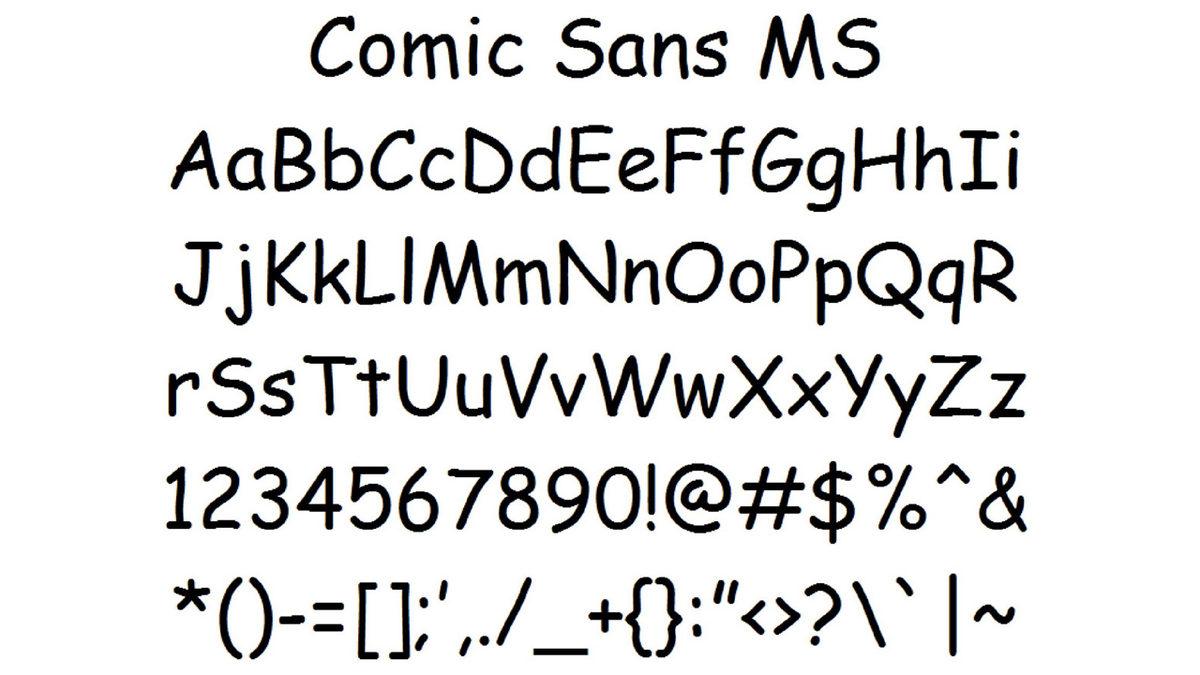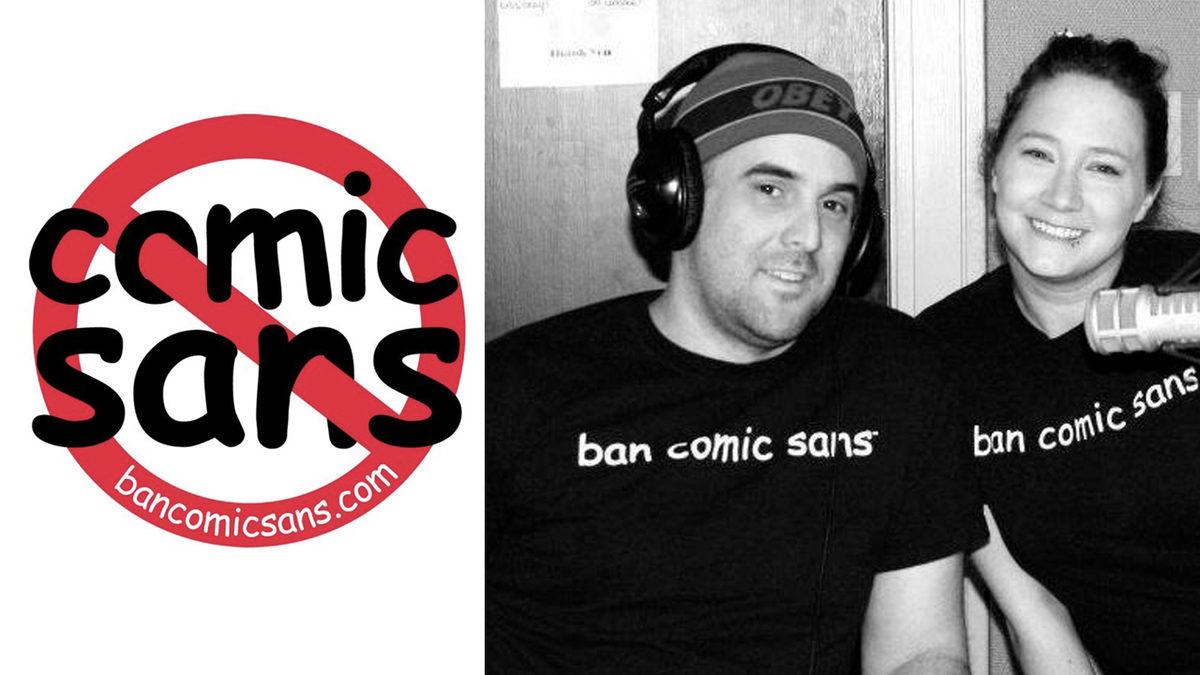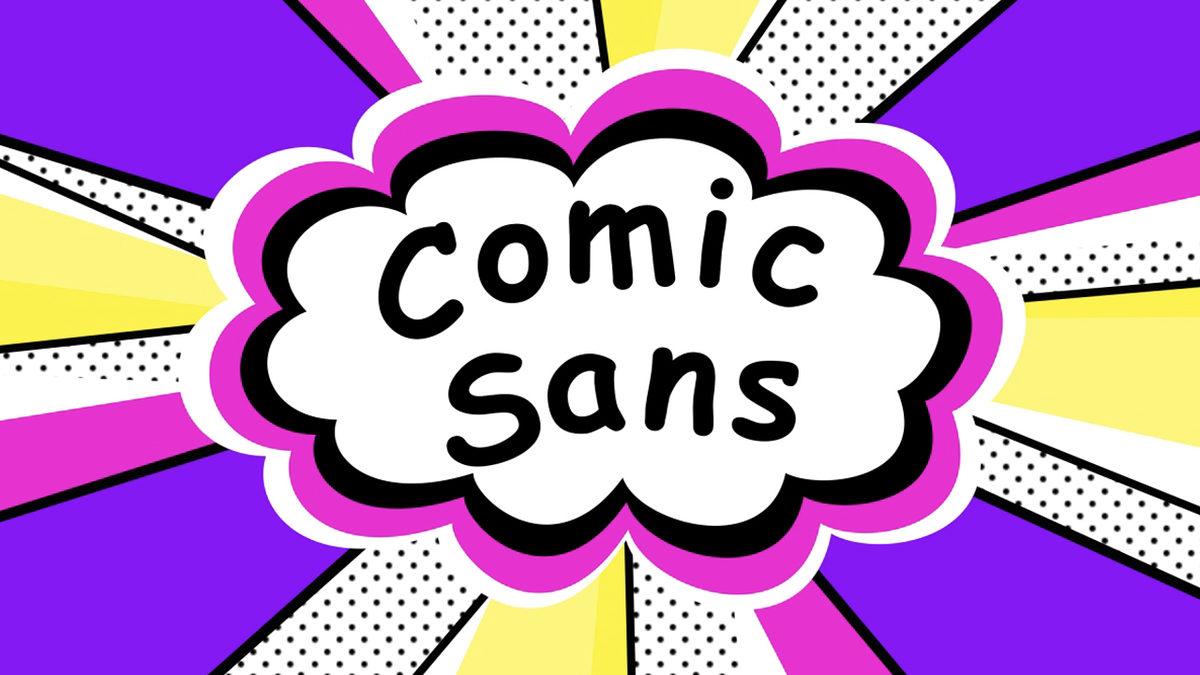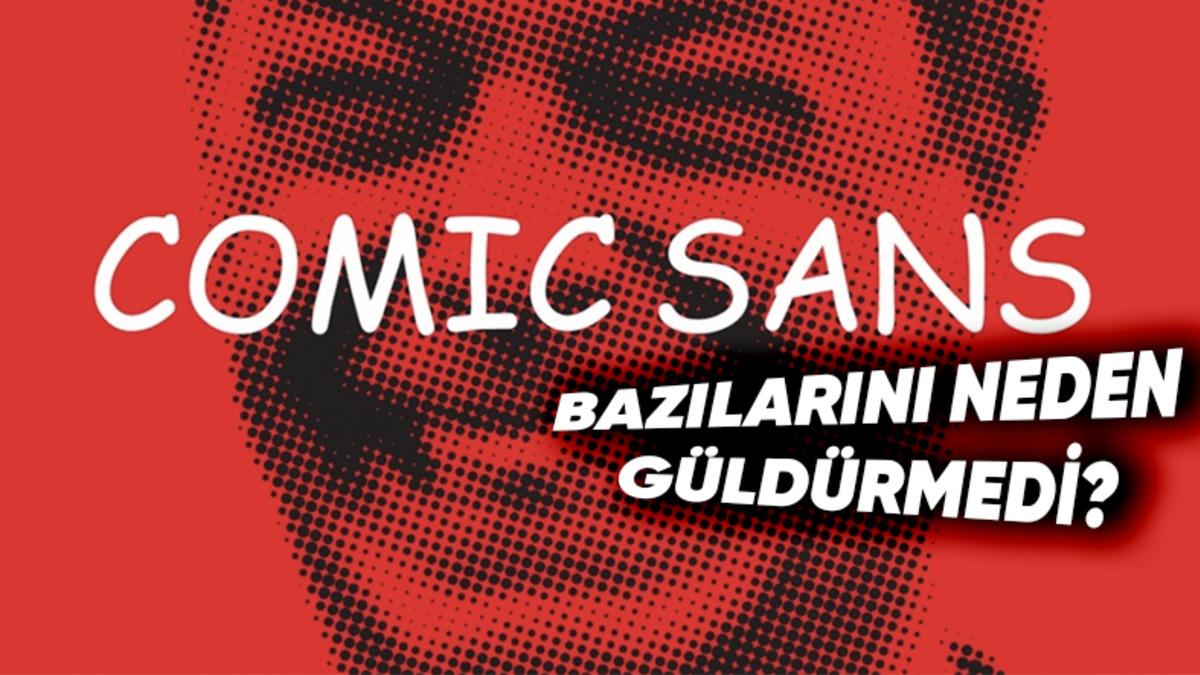
Pek çok kişinin gözünde bir kültür ikonuna dönüşen Comic Sans’ın da hikâyesi olur mu demeyin.
Bu sevimli ve çocuksu yazı tipinin ardında yatan serüvenden sonra sizin fikrinizi de merak ediyoruz.
Comic Sans, 1994’te Microsoft Bob ile ortaya çıktı.
Microsoft’ta tasarımcı olarak çalışan Vincent Connare, Microsoft Bob yazılımındaki köpek karakter Rover’ın konuşma balonları için kullanılan Times New Roman yazı tipinin çok ciddi olduğunu düşündü. Bunun için de yeni bir yazı tipi tasarladı.
Connare, yazı tipini oluştururken DC Comics'in "The Dark Knight Returns" ve "Watchmen" çizgi romanı karakterlerinin konuşma balonlarını inceledi. Comic Sans da tam olarak bu çizgi romanlardaki basit ve anlaşılır yazı stiline sahip olacak şekilde tasarlandı. Yazı tipinin amacı eğlenceli ve samimi bir hava yaratmaktı.
Bir anda popülerlik kazandı.
Comic Sans, Microsoft Bob’tan çok daha fazlası oldu ve birçok yerde kullanılmaya başlandı. Microsoft 3D Movie Maker’a eklendi ve açılır bütün pencerelerde, yardım bölmelerinde Comic Sans kullanıldı. Sonrasında da devam edildi ve Windows 95 Plus da artık Comic Sans’ı dahil etti.
Windows 95 OEM sürümünde standart yazı tipi olmasının üzerine ise artık Comic Sans, Microsoft Publisher ve Internet Explorer için varsayılan yazı tipi hâline geldi.
Varsayılan yazı tipi olmakla da kalmadı. Eğitim kayıtlarından parti davetiyelerine, iş yazışmalarından pankartlara kadar pek çok yerde Comic Sans görülmeye başlandı.
Ciddi olması gereken yazılarda bile kullanılması tasarım dünyasında rahatsızlık yarattı.
Comic Sans yaygınlaştıkça tasarım dünyasında âdeta bir "anti-kahramana" dönüştü. 2000'lerin başında Comic Sans'a karşı bir tepki olarak "Ban Comic Sans" hareketi bile başladı. Hareketin amacı yazı tipinin yanlış kullanımına dikkat çekmek ve daha uygun alternatifler önermekti. Ancak ironik bir şekilde, bu kampanya yazı tipinin daha popüler olmasını ve onun bir pop kültür fenomeninin dönüşmesine de olanak sağladı.
Nefretin nedenleri, estetik ve teknik açıdan bazı dezavantajlarının olmasıydı. Hem karakter aralığı tutarsızdı hem de özellikle büyük metin alanlarında gelişigüzel bir görünüme yol açıyordu.
Herkesin yazı tipine kimse karışamaz.
Comic Sans günümüzde sevimli görünümü ve okunaklı yapısı sayesinde özellikle çocuklar ve disleksi gibi okuma güçlüğü çekenler tarafından tercih edilen bir yazı tipi olmaya devam ediyor.
Bu yazı tipini sevip sevmemek tamamen kişisel bir tercih meselesi hâline gelmiş olsa da Comic Sans'ın tasarım ve tipografi dünyasındaki yerini koruduğu su götürmez bir gerçek. Comic Sans belki de "kötü" bir ürünün bile nasıl ikonik bir hâl alabileceğinin canlı bir örnek olarak tarih geçmiş durumda.